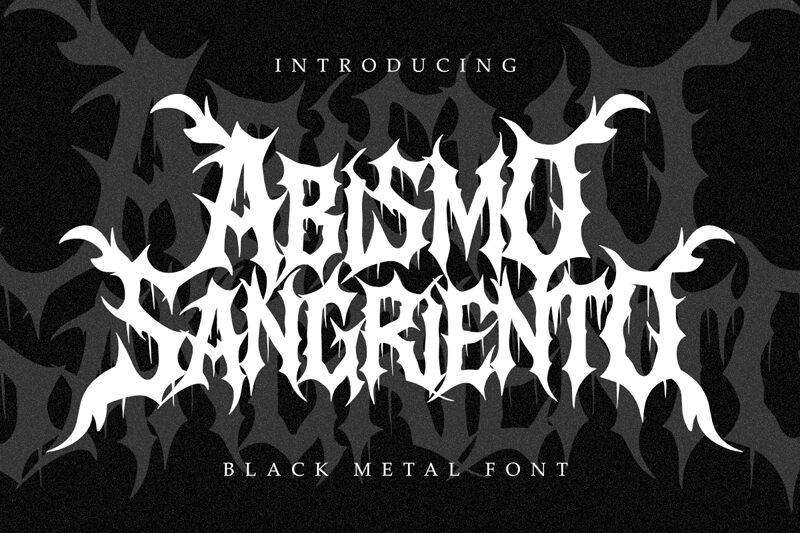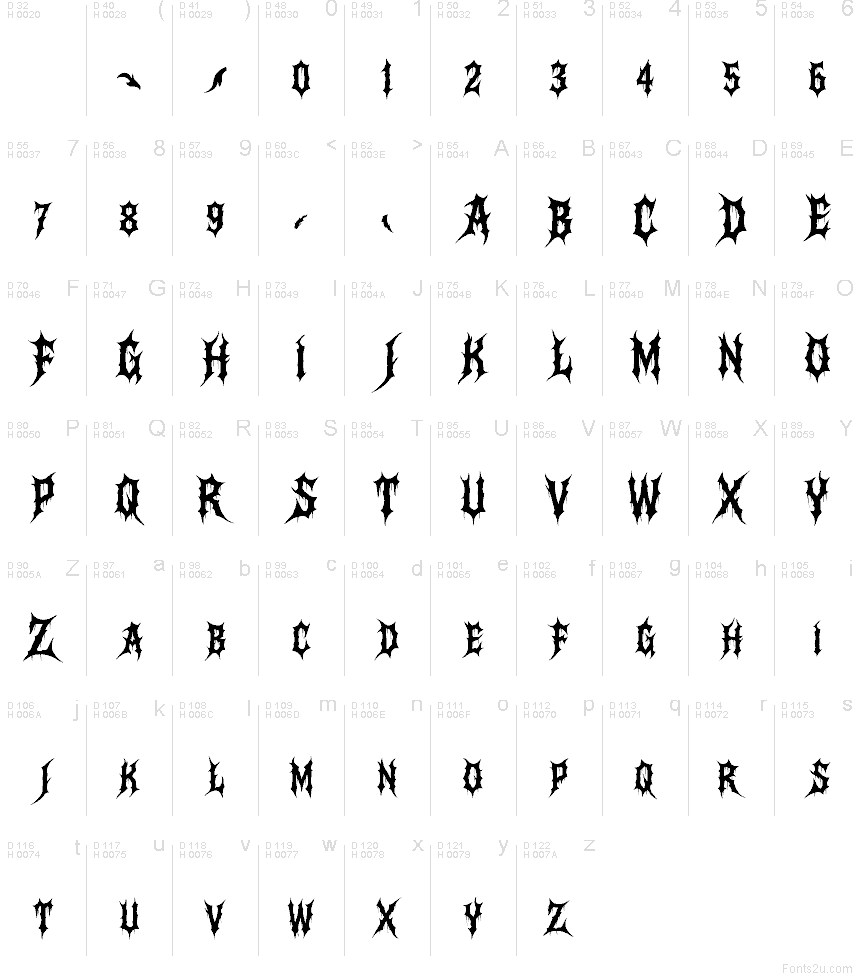
Písmo Abismo Sangriento od Masyafi Studio je bezplatný gotický font s ostny připomínajícími trny, lomenými tahy a ostrými, nepravidelnými okraji, které dodávají každému písmenu drsný, rituální vzhled. Tvary jsou těsně seskupené, s ostrými řezy a úzkými otvory, díky nimž znaky vypadají jako vytesané, nikoliv psané.
Abismo Sangriento se skvěle hodí na plakáty heavy metalu, hororové tituly, návrhy tetování, obaly alb, letáky akcí a temný branding, protože jeho rozbité obrysy v krátkých textech přenášejí agresivní, řemeslnou energii. Tento bezplatný font se také hodí pro logotypy, samolepky a dekorativní nadpisy, pokud hledáte písmo, které působí syrově, přísně a je stylizované pro temná témata.